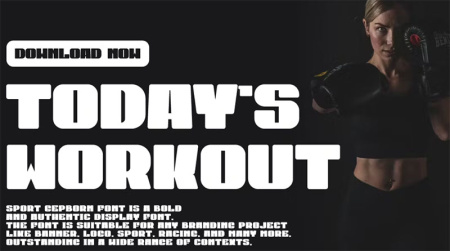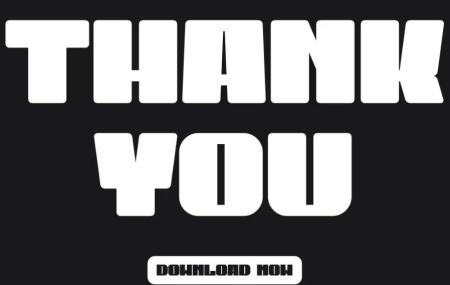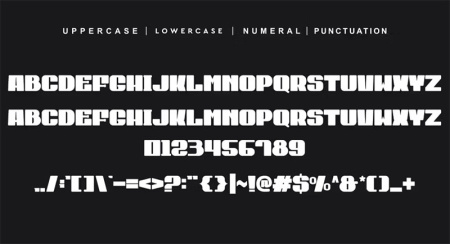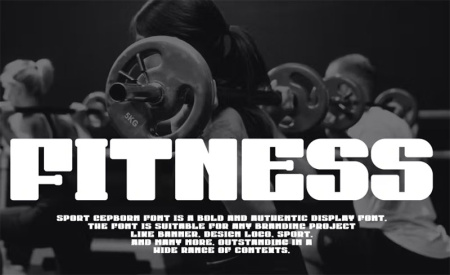
دانلود فونت اسپرت انگلیسی Sport Gepborn
دانلود فونت اسپرت انگلیسی Sport Gepborn یک فونت اسپرت و ورزشی زیبا است. این فونت برای هر پروژه برندسازی مانند لوگو، چاپ تی شرت، ورزش و بسیاری موارد دیگر مناسب است. برای دانلود فونت اسپرت و مشاهده تصاویر این فونت از gfxdownload.ir با ما در ادامه مطلب همراه باشید.
دانلود فونت انگلیسی اسپرت Sport Gepborn
دانلود فونت انگلیسی ورزشی Sport Gepborn
دانلود فونت اسپرت Sport Gepborn
دانلود فونت اسپرت و ورزشی Sport Gepborn
دانلود فونت اسپرت و ورزشی انگلیسی Sport Gepborn